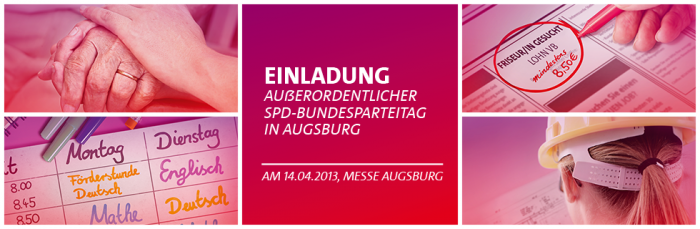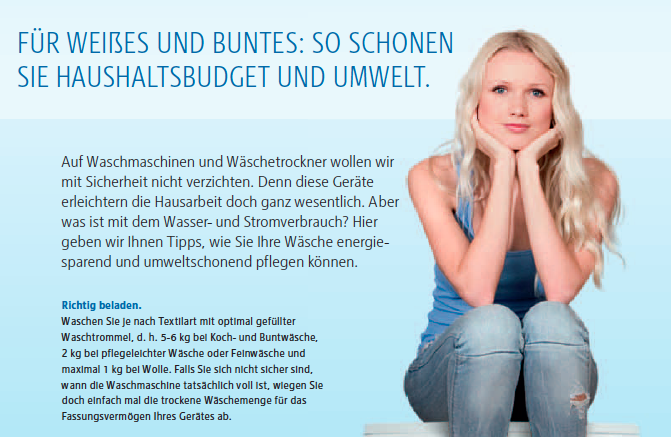
Aber das ist doch kein Problem des Versal-Eszetts, oder? Was liest denn jemand, der das Eszett nicht kennt, wenn er das gemischt geschriebene Wort »Weiß« sieht?
Das gemeine ß ist wenigstens seit ein paar Jahrzehnten bekannt, daher gehe ich davon aus, dass es weniger Probleme macht als das ẞ. Aber du hast Recht, ß und ẞ stiften Verwirrung. In diesem Punkt sind mir die Schweizer sympathisch, die haben es einfach abgeschafft. :-)
Mich überzeugen die Qualitäten des Versal-Eszett(s) und deswegen werde ich es nach Möglichkeit verwenden. Mögliche Verwechselungsfehler sollten die Schriftgestalter beflügeln, die Gestaltung von B und ẞ eindeutig zu halten. Ich wünsche mir, dass solch ein Manko nicht zu mangelnder Akzeptanz der sinnvollen Ergänzung des Alphabets um das ẞ führt. Erst wenn bertel restlos vom ẞ überzeugt ist, haben wir es geschafft!  ;-)  ;-)  ;-)
dass das ẞ eben nicht der Verständlichkeit dient, sondern eine weitere Fehlerquelle aufmacht
Welche Fehlerquelle? Das Gegenteil ist doch der Fall. Fehlerquellen werden abgeschafft.
Das gemeine ß ist wenigstens seit ein paar Jahrzehnten bekannt, daher gehe ich davon aus, dass es weniger Probleme macht als das ẞ.
Dass Fortschritt auch mit Lernen/Umdenken einhergeht, liegt auf der Hand. Irgendwann gab es mal gar kein Alphabet. Ist das jetzt ein Grund unsere heutige Schriftsprache zu verwerfen?
Das genaue Gegenteil ist der Fall – wenn du einen Buchstaben nicht kennst, kannst du ihn auch nicht lesen. Und je nach Form steht dann WEIB statt WEIẞ. Aber das hatten wir ja alles schon durchgekaut ;-)
Das wiederum, ist ein ziemlich zusammenkonstruierter Einzelfall. Jemand soll einen deutschen Namen lesen, ohne Deutsch zu können und dann einen anderen hineininterpretieren, der wiederum zufällig ein deutsches Wort erzeugt.
Ja. Ist möglich. Aber das ist jetzt ein plausibler Grund, dass 90 Millionen auf Jahrzehnte oder Jahrhunderte lieber einen Sinn tragenden Kleinbuchstaben durch zwei Sinn tragende Großbuchstaben ersetzen, die wiederum wahlweise für sich oder für diesen einzelnen Buchstaben stehen? Nur damit Familie Weiß niemals einen Brief als Familie Weib erhält? (Sondern gegebenenfalls lieber in der ebenfalls falschen Schreibung Weiss)
Mhh. Klingt jetzt nicht so richtig plausibel im Sinne des Gesamtsachverhaltes.
Wenn der Ami das ß durch ein B ersetzt
Ohnehin macht »der Ami« das nach meinen Erfahrungen keinesfalls öfter als »der Michel«, der sich z.B. seit Jahrzehnten weigert, das Ł im Namen meiner Oma zu schreiben.
Ich habe es nach der Geburt meiner Tochter kürzlich wieder erlebt. Auf allen Krankenhausdokumenten waren die Diakritika in den Namen von Mutter und Tochter drauf; in der vom Krankenhaus automatisch geschalteten Zeitungsanzeige auch. Besondere Klimmzüge unsererseits erforderte das nicht. Ich habe ein einziges Formular per Hand ausgefüllt, und alle Diakritika wurden ungefragt übernommen. In der automatisch erstellten Geburtsurkunde stehen im ersten Anlauf keine Diakritika, aber das liegt an der EDV im Gesundheitsministerium. Wenn wir möchten, können wir das (halb-manuell) korrigieren lassen. Nur beim US-Pass ist Schluss, da werden nie Diakritika verwendet. (Das kann ich auch irgendwo verstehen. Wegen des Gleichheitsgebots müssten, sobald ein Diakritikum erlaubt ist, ALLE erlaubt sein – und den Zeichensalat normalisierbar zu verwalten wäre ein echter Albtraum.)
Wegen des Gleichheitsgebots müssten, sobald ein Diakritikum erlaubt ist, ALLE erlaubt sein – und den Zeichensalat normalisierbar zu verwalten wäre ein echter Albtraum.
Nö. Dank Unicode ist dies eigentlich kein Problem mehr, denn dort ist die Normalisierbarkeit gewährleistet. Unicode garantiert auch, dass eine normalisierte Form in allen zukünftigen Versionen des Standards unverändert bleibt.
In ähnlicher Art und Weise garantiert Unicode, dass ein ß einem SS zugeordnet wird, und zwar auch in allen zukünftigen Versionen des Standards. Sollte dereinst einmal die Zuordnung von ß zu in einem neuen Rechtschreibreförmchen vorgeschrieben werden, so wäre dies trozdem mit Unicode vereinbar, denn Unicode sieht neben den Default-Zuordnungen auch die Möglichkeit von zusätzlichen massgeschneiderten Zuordnungen vor, die unter bestimmten Umständen an Stelle der Default-Zuordnungen gelten. Ein Beispiel ist die massgeschneiderte Zuordnung von i zu İ, die in türkischen Texten an Stelle der Default-Zuordnung von i zu I gilt. In ähnlicher Art und Weise könnte für deutsche Texte die massgeschneiderte Zuordnung von ß zu an Stelle der Default-Zuordung von ß zu SS gelten.
Dank Unicode ist dies eigentlich kein Problem mehr, denn dort ist die Normalisierbarkeit gewährleistet.
Das eigentliche Problem liegt ganz woanders, nämlich an der traurigen Tatsache, dass ganz normale Menschen mit einem solchen System arbeiten müssen. Selbstverständlich wäre ein System, das jegliche Diakritika erlaubt, ein kompletter Albtraum, ganz unabhängig von Unicode. Das fängt schon damit an, dass es keine vernünftigen Eingabemethoden für alle Unicodezeichen gibt (oder auch nur alle, die auf lateinischen Buchstaben basieren). Dann müssten Buchstaben mit beliebigen Diakritika auch von Sachbearbeitern, die nicht alle Sprachen mit lateinischen Alphabeten sprechen, erkennbar sein, auch in handschriftlich ausgefüllten Formularen. Das geht natürlich auch nicht. Man denke nur an Unterschiede zwischen ş und ș, đ und ð usw. usf.
Unicode garantiert auch, dass eine normalisierte Form in allen zukünftigen Versionen des Standards unverändert bleibt.
In ähnlicher Art und Weise garantiert Unicode, dass ein ß einem SS zugeordnet wird, und zwar auch in allen zukünftigen Versionen des Standards. Sollte dereinst einmal die Zuordnung von ß zu in einem neuen Rechtschreibreförmchen vorgeschrieben werden, so wäre dies trozdem mit Unicode vereinbar, denn Unicode sieht neben den Default-Zuordnungen auch die Möglichkeit von zusätzlichen massgeschneiderten Zuordnungen vor, die unter bestimmten Umständen an Stelle der Default-Zuordnungen gelten.